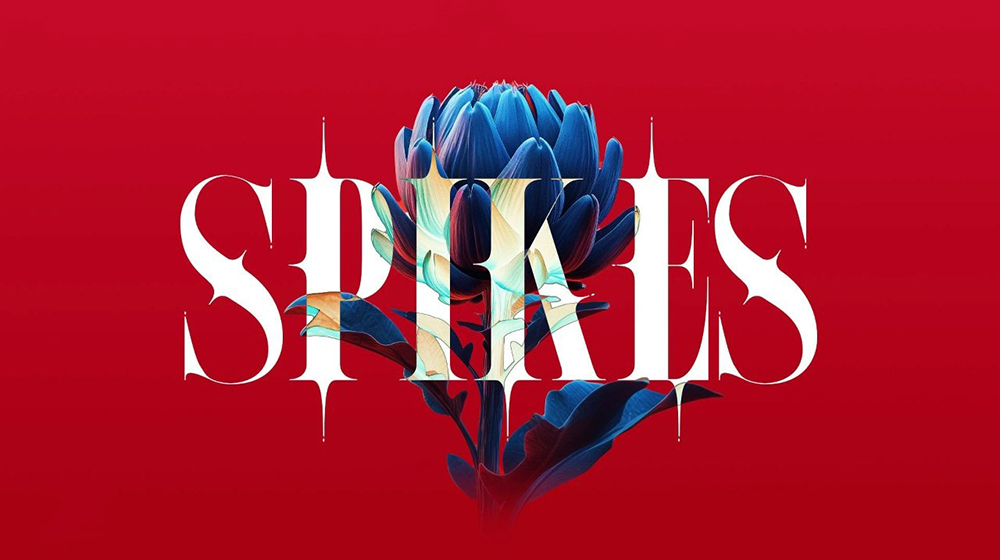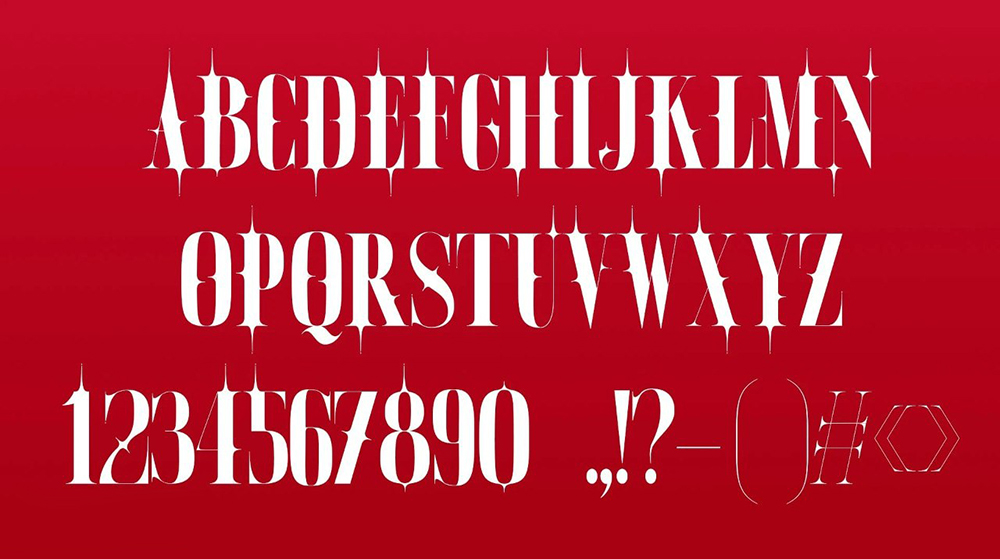
دانلود فونت انگلیسی Spikes Font
فونت پرمیوم و انگلیسی Spikes Font یک فونت نمايشی و فانتزی است. اين فونت برای هر پروژه برندسازی مانند لوگو و… مناسب است.
مزایای استفاده از فونت لاتین Spikes چیست؟